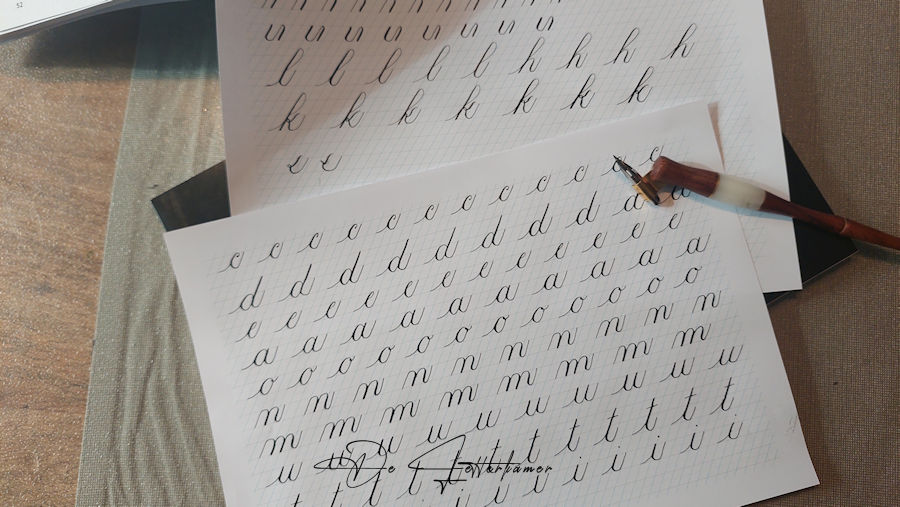
Kalligrafie is een perfecte bezigheid om even tussendoor je gedachten op stil te zetten, even uit zetten. In de “off” fase. Even stilstaan in deze toch wel razend snelle wereld. Een wereld die heel snel gaat, te snel als je het mij vraagt. Ik heb mijn wekelijkse gewoonte op een avond mijn kalligrafie spullen boven te halen, neem mijn boek bij de hand, een zeer handig boek trouwens. Mijn oblique penhouder waarmee ik vrij vlug begon te oefenen, en overigens geen seconde spijt van heb gehad. Het is de prijs waard. Deze heb ik gekocht bij Splendith.
De vorige keer ging het me niet, dus mijn 2de poging voor groep 1 (i, t, u, m, n) en groep 2 (o, a, e, d, c)
Eerst mijn hand opgewarmd om de handeling er in te krijgen, zonder gaat dus niet, je maakt vrijwel meteen fouten. Toch als beginneling.
Daarna heb ik een paar letters gedaan van Deel 3: en daar zag ik de “lussen” staan die ik toch niet gemakkelijk vind. En die letter “k”, daar ga ik moeten op oefenen, véél moeten op oefenen. In groep 3 zijn het de volgende letters: l, h, k, b, f.
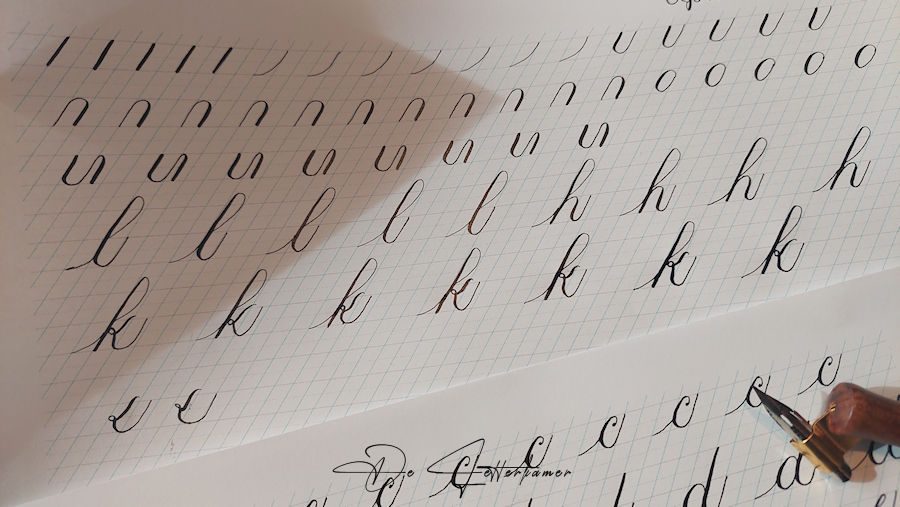
Dit is mijn oefenblad, waar ik alles door elkaar schrijf.
Zo, ik ga afronden, de volgende keer ga ik beginnen met groep 3.